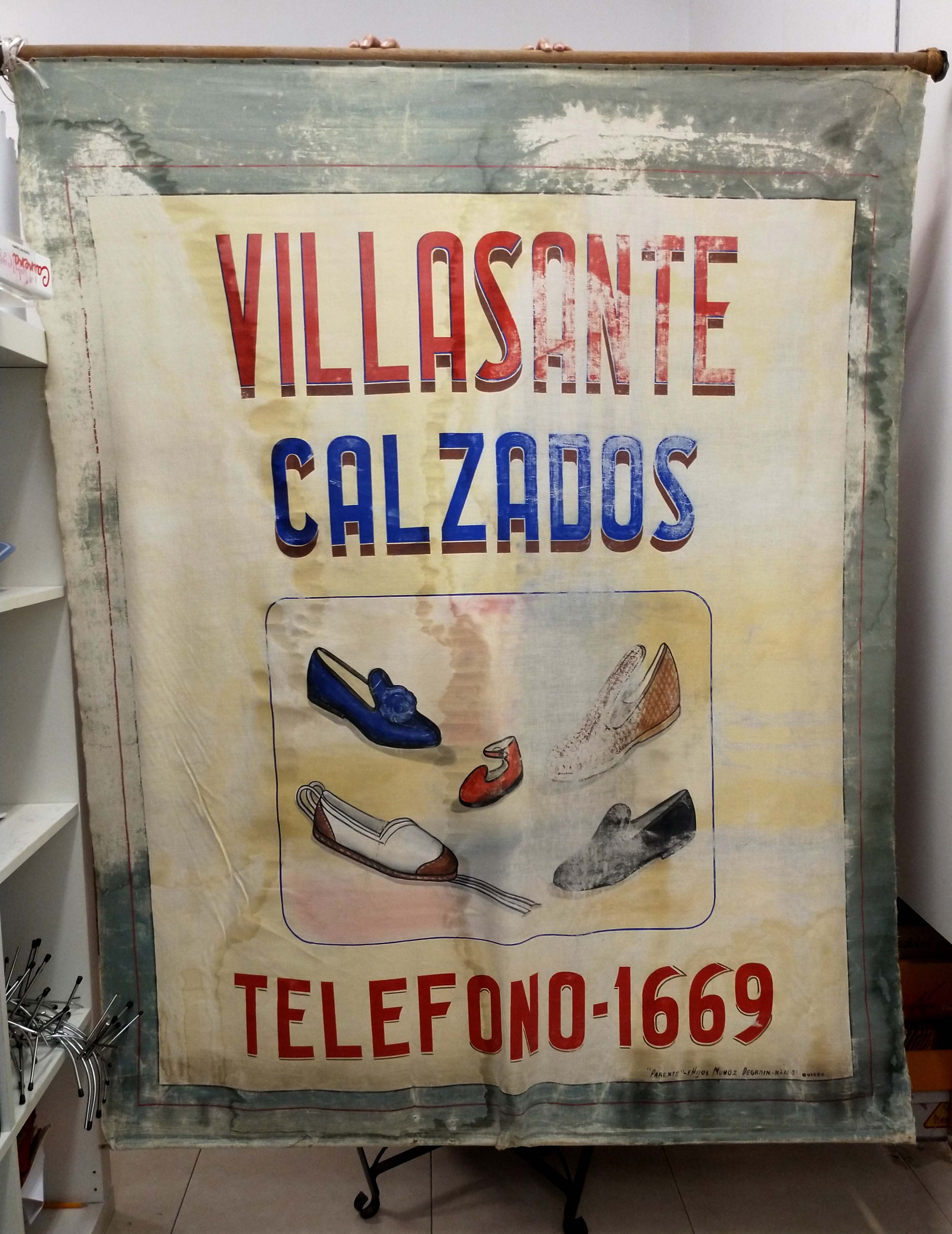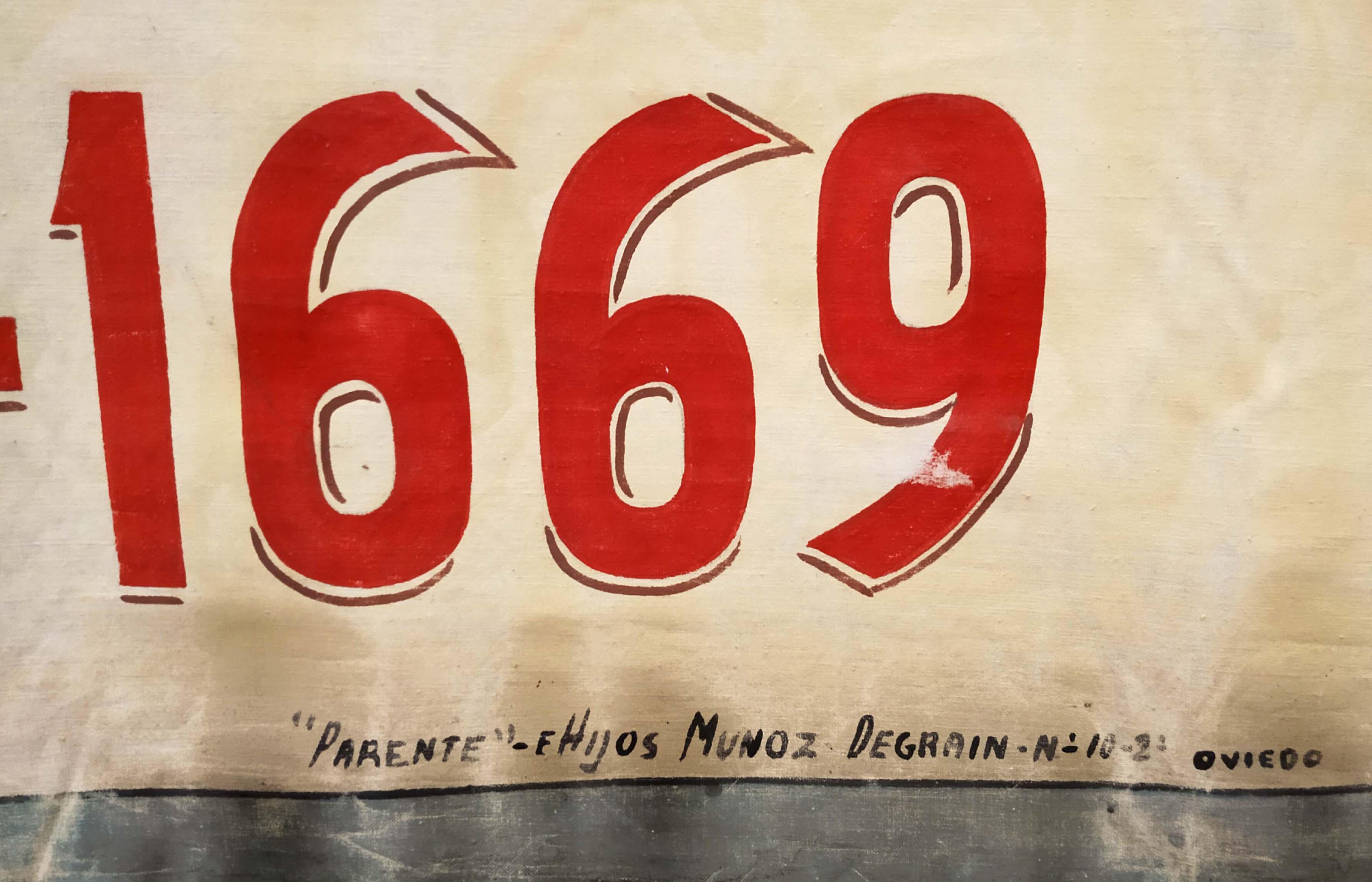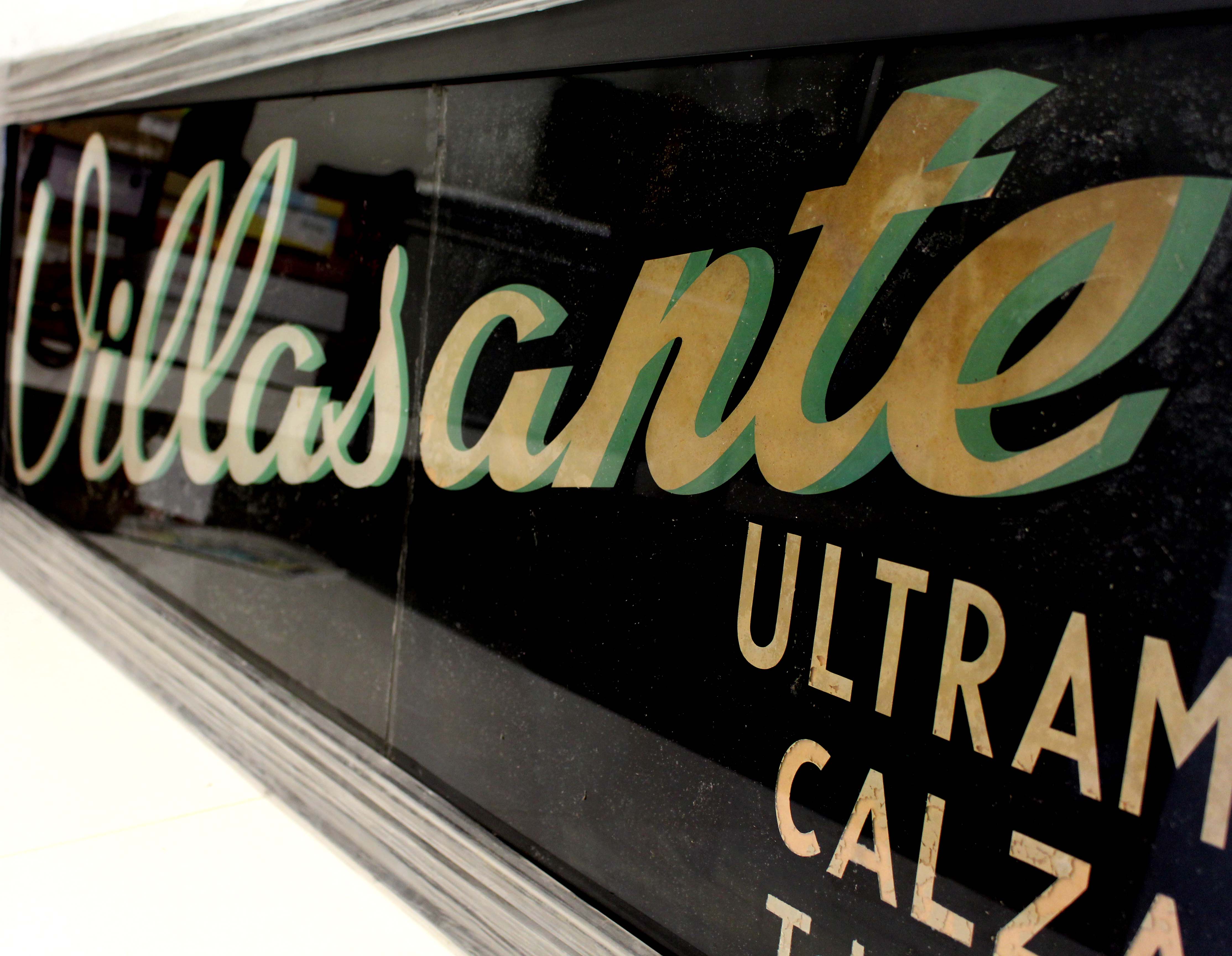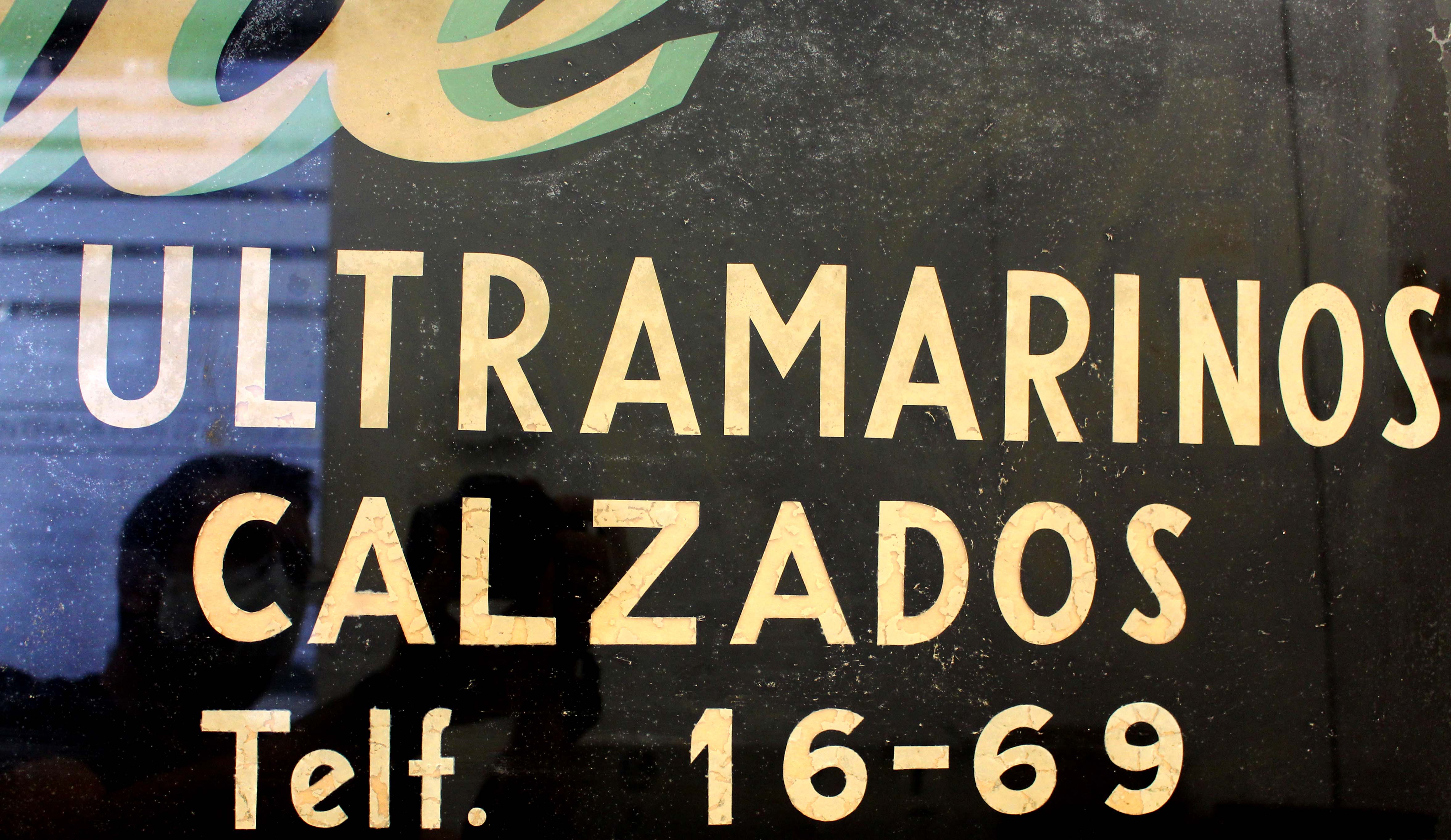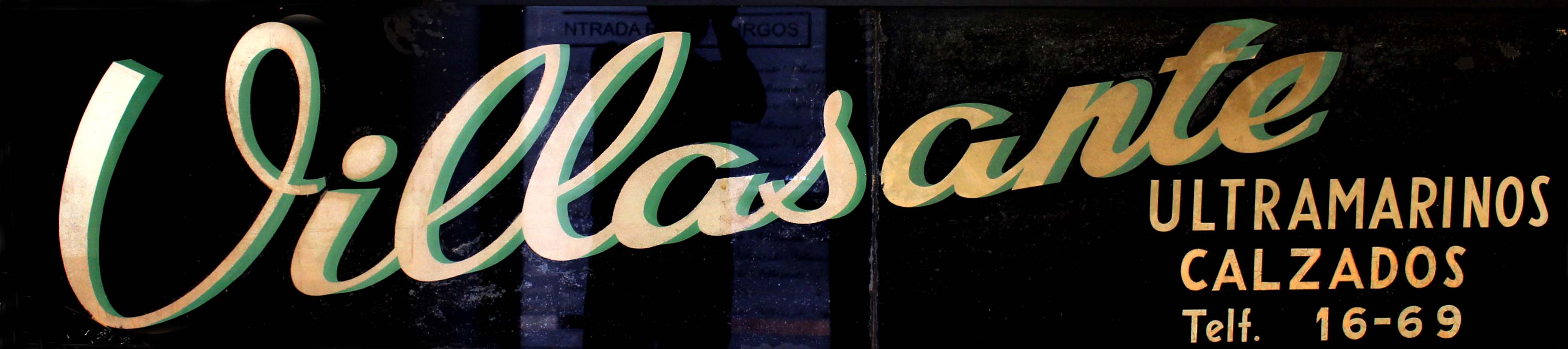
Calzados Villasante
Rescatar la memoria de comercios que han estado ahí siempre, pero que muchas veces pasan desapercibidos sea por cambios de hábitos, por su aspecto exterior u otros factores, hace que cuando sale a luz un elemento tan identitario como es un rótulo de las trastiendas, es un momento único, porque sale a la luz la historia del comercio.
“Calzados Villasante” es un comercio familiar que actualmente está gestionado por la tercera generación, Charo y Begoña Fernández Villasante. Son nietas de los fundadores, sus abuelos Mariano y Dionisia; que dejaron Villasante (Burgos) para venirse a Santander a finales de la década de los años treinta, e instalar un pequeño negocio de Ultramarinos debajo de su casa en la Cuesta del Hospital. Pero el incendio de febrero de 1941 les afecto llevándose por delante el negocio e instalándose posteriormente en los famosos barracones. Ya en Julio de 1943 se instalan en el local actual de la calle Burgos, y es aquí cuando más adelante comienzan a vender zapatillas y alpargatas, ante una demanda constante, por lo que poco a poco el negocio va diversificándose. Desde entonces ha sido una de las zapaterías más tradicionales y de comercio generacional de Santander, de los cuales son pocos que aún perduren en nuestras calles.
El rótulo tiene unas dimensiones de 210 x 50 cm. No se ve firma del taller que lo realizó; probablemente quede tapado por el marco que se la puesto actualmente para su protección. “Ultramarinos y Calzados” resumen de lo contado anteriormente y acompañados de un teléfono de cuatro cifras 16-69, que nos da esa información temporal necesaria para poder acotar su época. En Santander tenemos otros 2 ejemplo de este tipo de número de teléfono: “Las Tres M” y “Frutería Mary”. También que sea de vidrio el rótulo, lo hace como pieza excepcional artesanal, y se suma así otros pocos ejemplos que aún perduran a pie de calle.
Por otro lado, hay un precioso telón de escaparate dibujado artesanalmente y que viene firmado por el taller ovetense de “Parente” e Hijos. José Parente, fue un cartelista conocido en Asturias en los años 50, que junto a otros artistas crearon un estilo particular en la publicidad comercial asturiana (1).
Es por ello por lo que el valor de este patrimonio gráfico no sólo radica en su estética como objetos, si no en la parte inmaterial de todo ello, en la memoria local. Además de dotar de valor añadido a un comercio con más de 70 años de trayectoria e historia ininterrumpida.